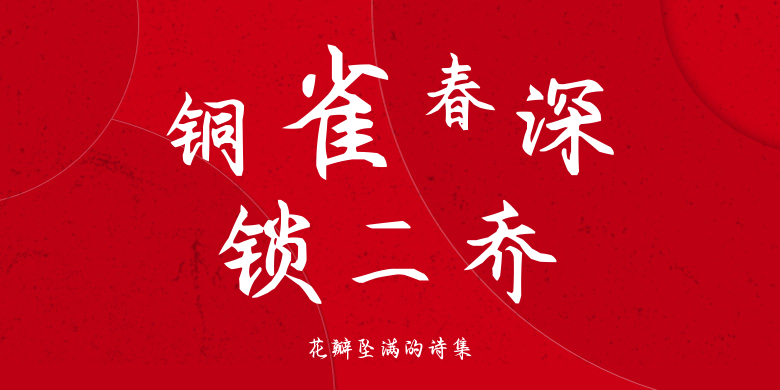
花瓣坠满的诗集
花瓣坠满的诗集,这款字体结构工整、笔画清晰,兼顾美观与易读性,适用于标题、正文、海报、包装、LOGO 等多种场景。字形优雅稳定,风格百搭耐看,适配日常排版与创意设计,让文字呈现更舒适、更具质感。花瓣坠满的诗集一笔一画,皆是细节,以均衡的比例、流畅的线条打造舒适视觉体验,字形端正大气,风格简约现代。无论是商业设计、品牌宣传还是日常排版,都能轻松驾驭,让文字更有格调与力量。花瓣坠满的诗集字体下载。